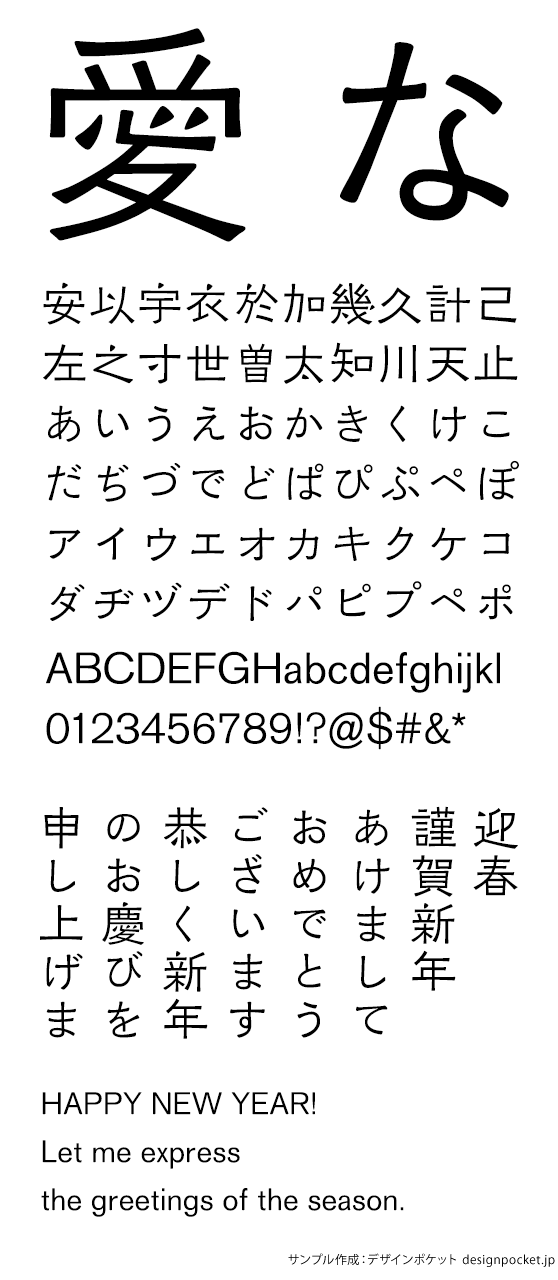
KOくれたけ銘石M
KOKuretakeMeiseki-M
『活版総覧』(森川龍文堂、1933)に掲載されている「十二ポイント角呉竹」の組み見本から復刻した「くれたけ」に、『王興之墓誌』(341)と『王興之妻宋和之墓誌』(348)にもちいられた字様をもとに翻刻した「銘石」、1898年にドイツ・ベルリンのベルトルド活字鋳造所が製作した「アクチデンツ・グロテスク」をベースにした「K.E.Sagittarius」を組み合わせた「KOくれたけ銘石B」のファミリーで、メディウム・ウエイトです。